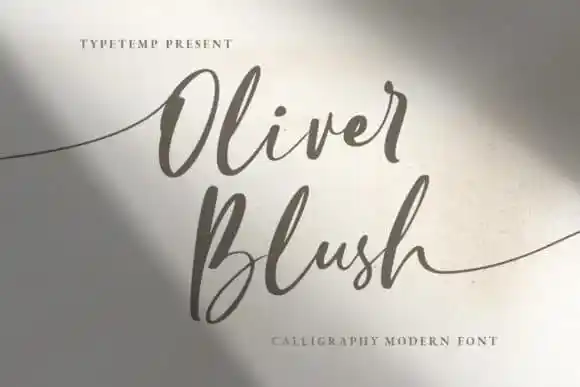
Oliver Calligraphy Font – Download Grátis
A fonte “Oliver Calligraphy Font” é uma delícia para os olhos, oferecendo a sensação de frescura e modernidade encontrada na tipografia delicada e elegante. Ideal tanto para designers digitais quanto para aqueles que desejam adicionar um toque romântico e autêntico em seus projetos. Desenvolvida pelo designer TypeTemp Studio, esta fonte foi criada como uma opção relaxada e contemporânea para quem busca expressar a essência de uma escrita à mão livre. Seja ela usada em cartões de agradecimento, gráficos decorativos ou até mesmo em sites, “Oliver Calligraphy Font” é perfeita para aqueles que buscam um blend harmonioso entre o clássico e o moderno, tornando qualquer projeto mais atraente e singular.